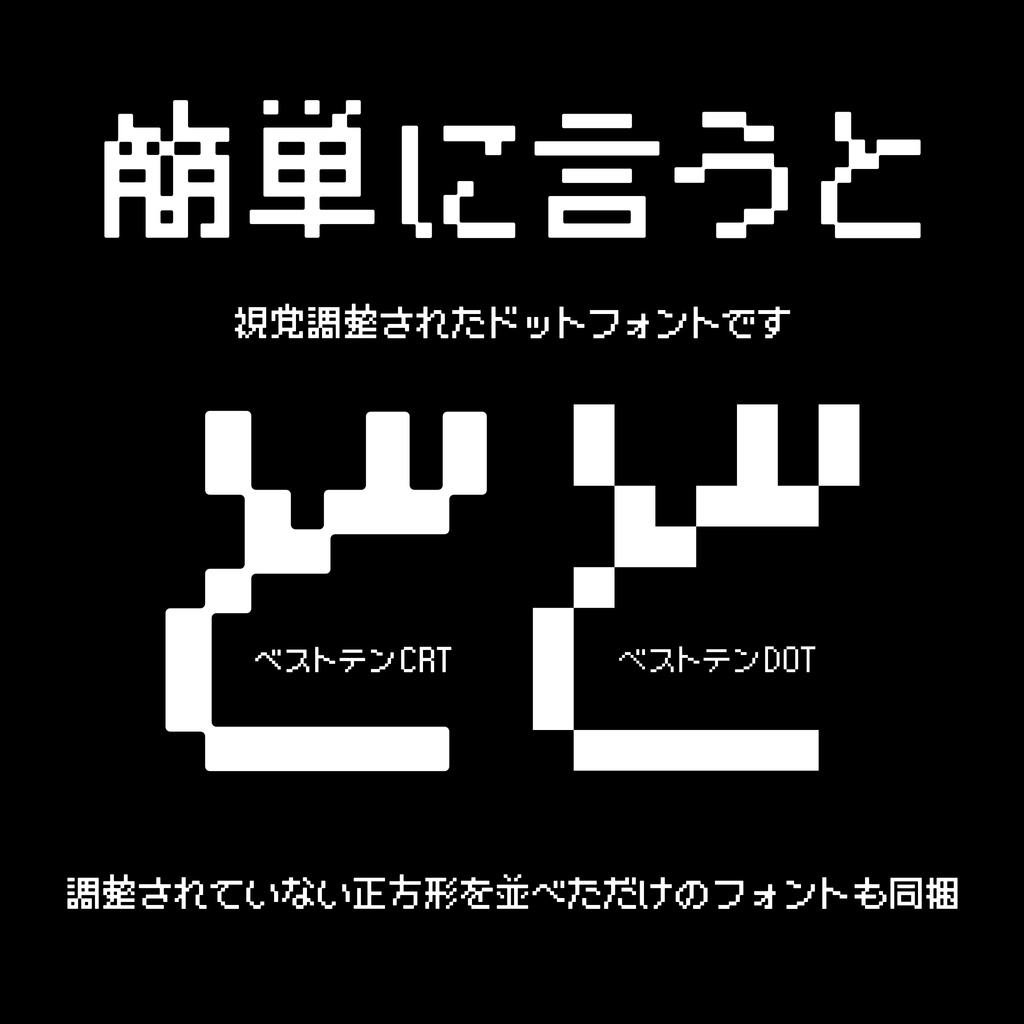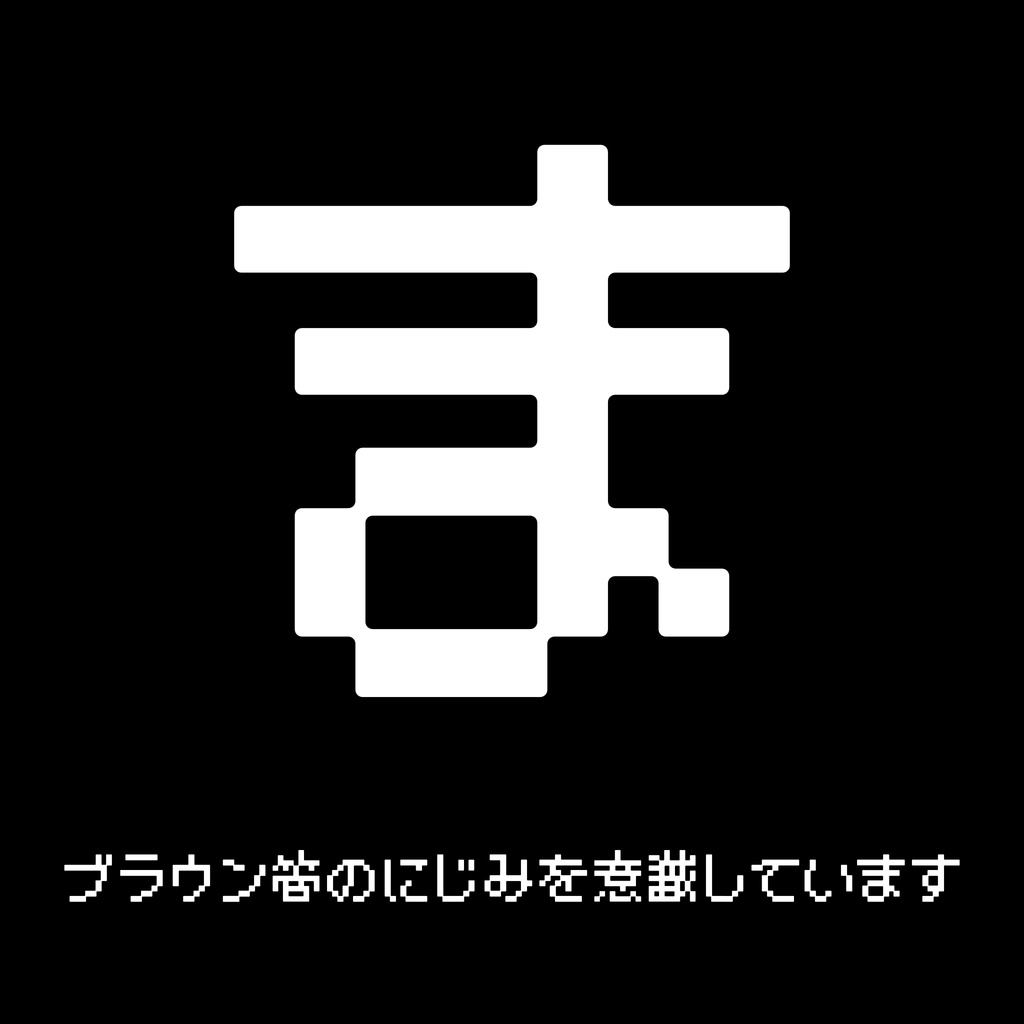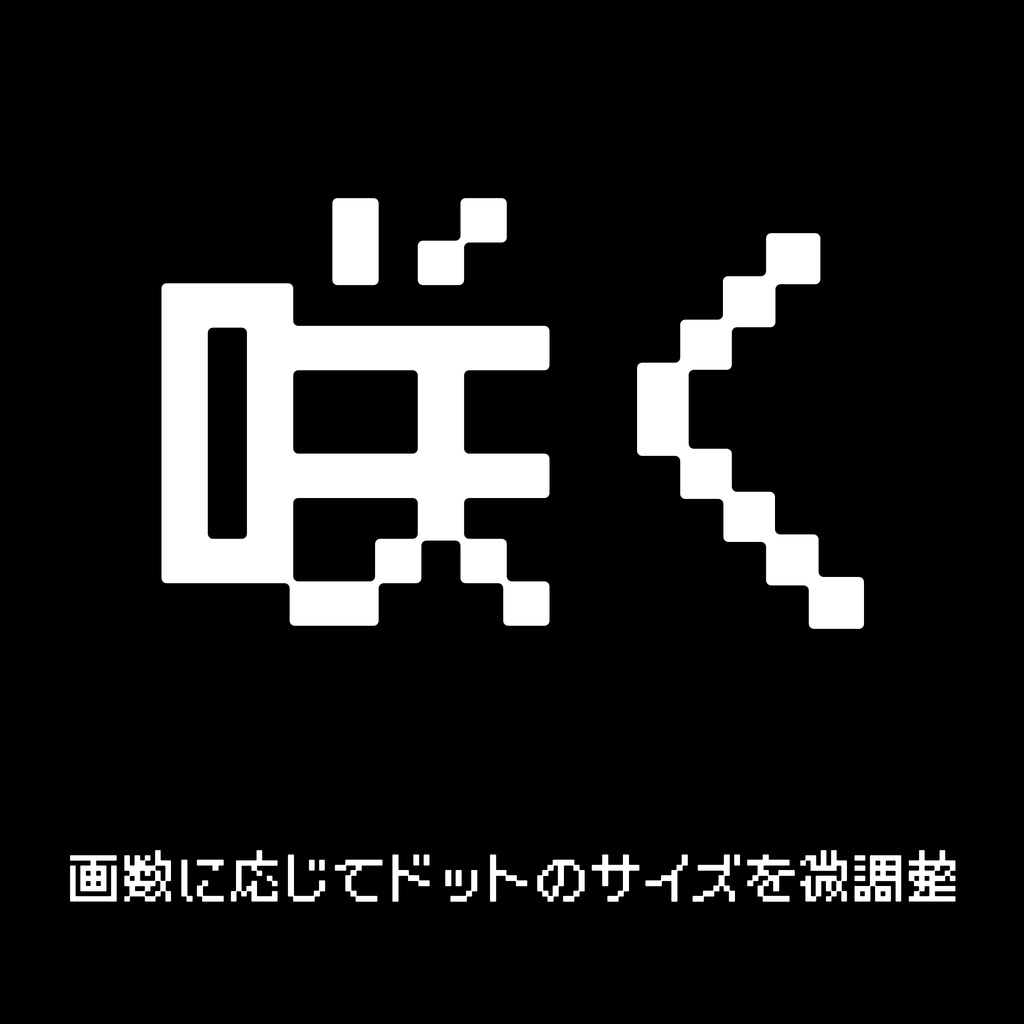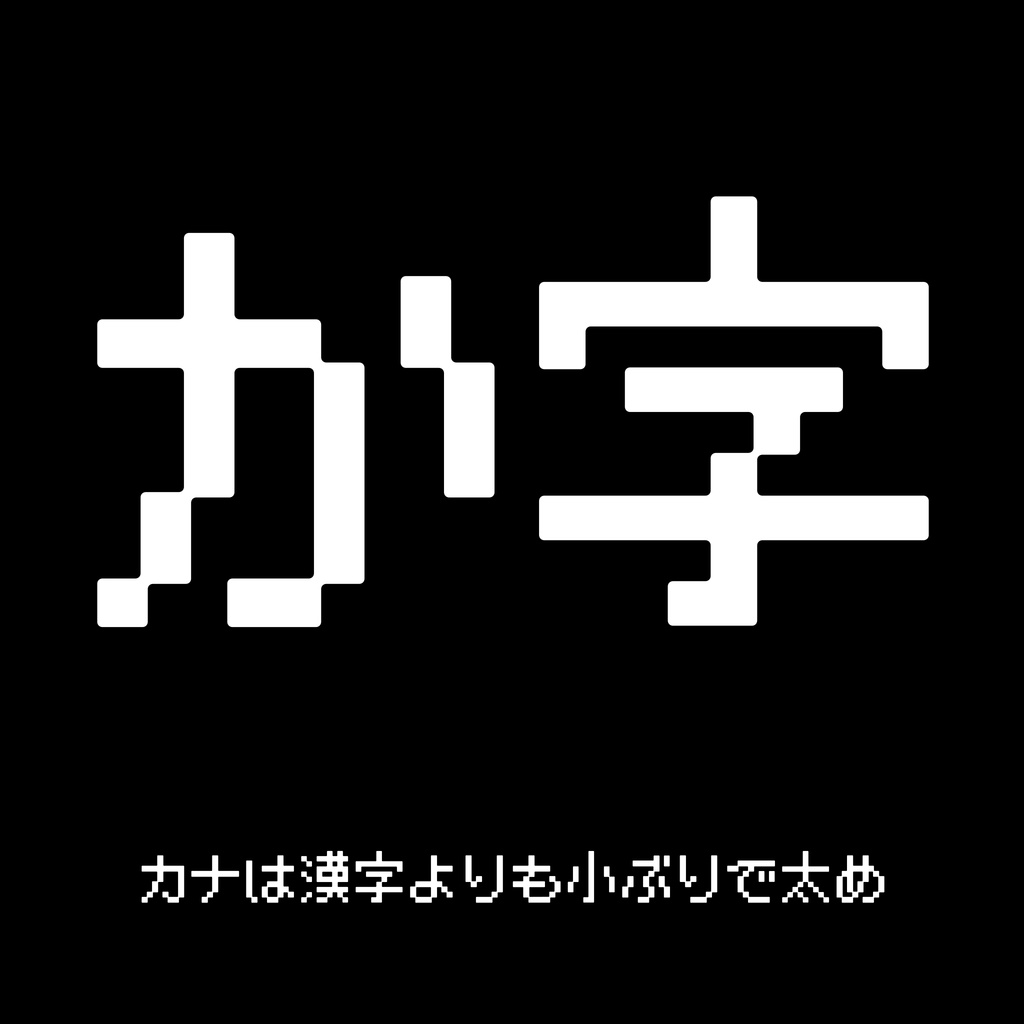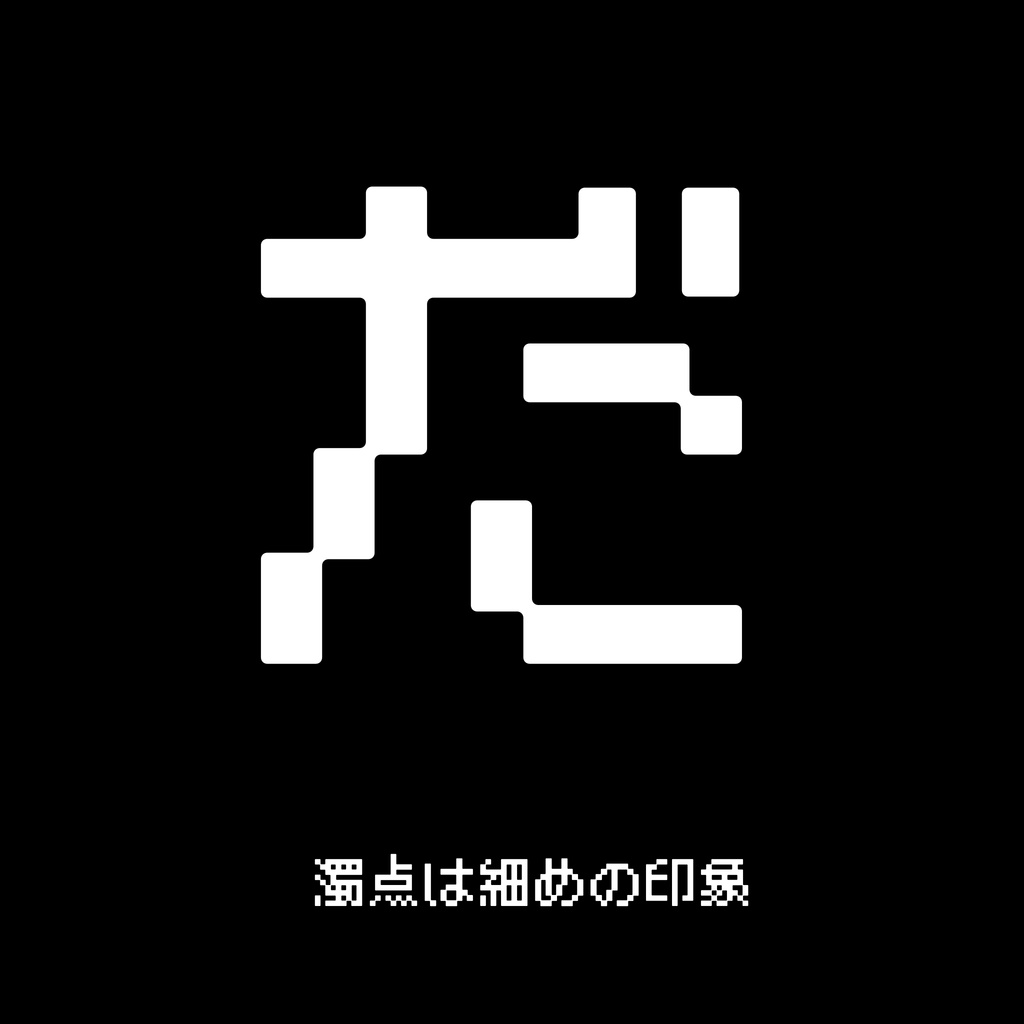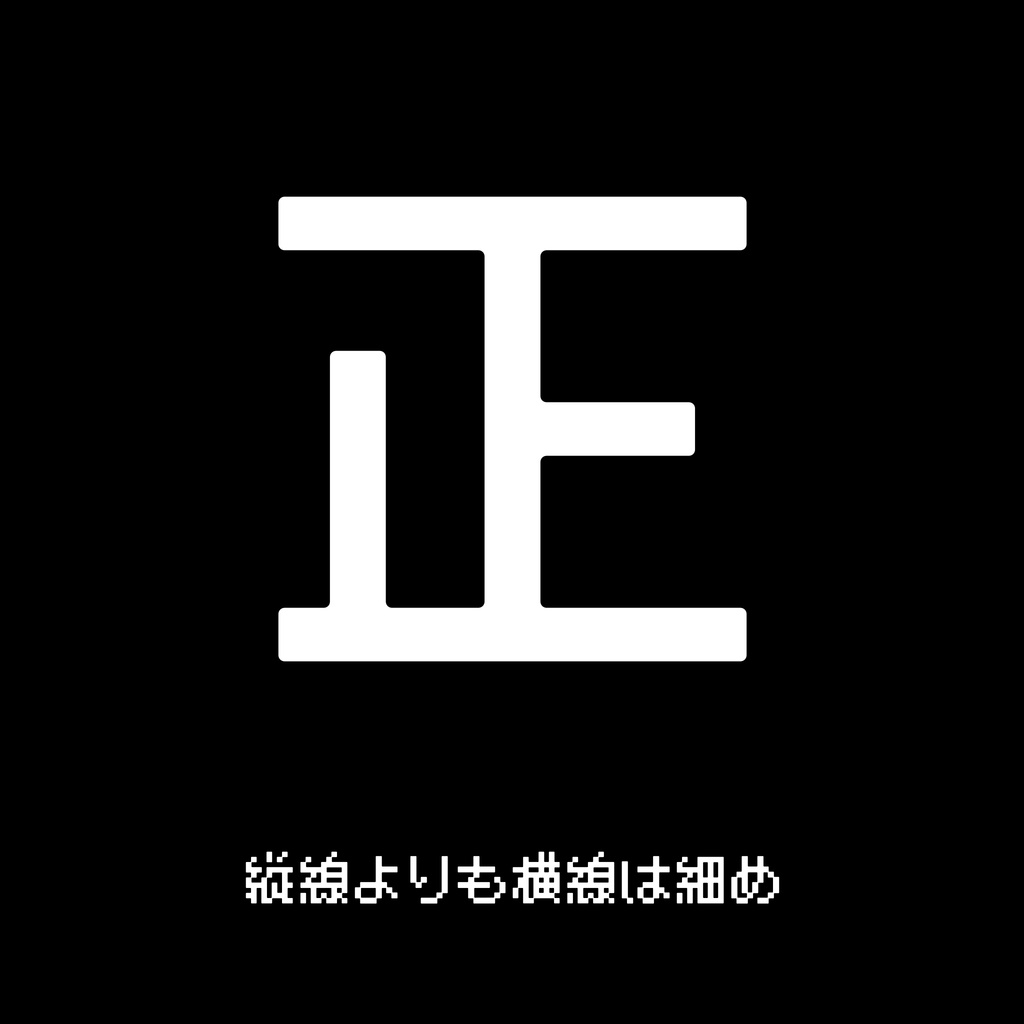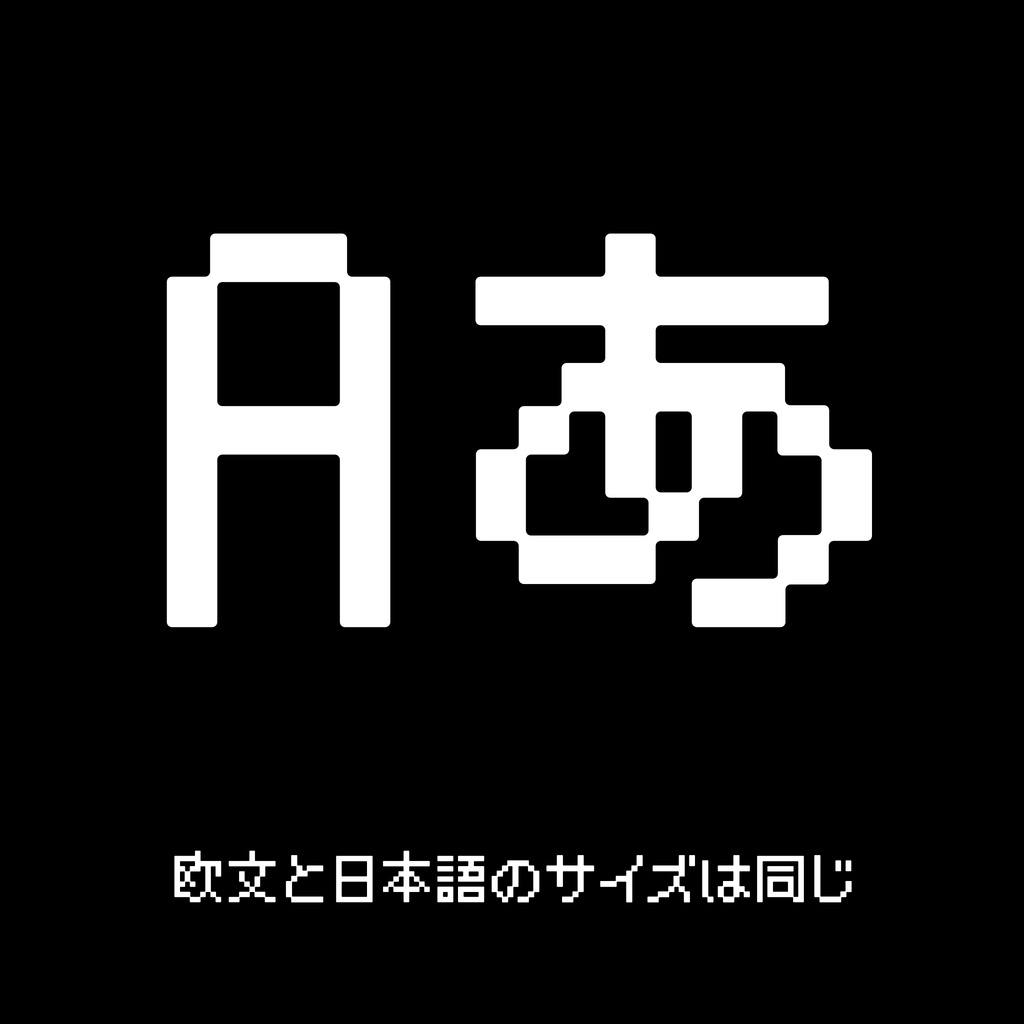
ベストテンFONT フリーフォントのベストテンは無料でダウンロードできるドットフォント。商用・非商用問わず使用可能なので、安心してダウンロードしてください。 【特徴】 10×10のドットフォント。視覚調整と加工のされたベストテンCRTと、ドットを並べただけのベストテンDOTの2種類。簡単に言うとそのまま使うだけでレトロなゲームやコンピューターっぽくなるベストテンCRTと、純粋にドットフォントとして使えるベストテンDOTのセットです。 ひらがな、カタカナ、欧文をオリジナルで制作し、残りの部分をM+ BITMAP FONTSの派生フォントPixelMplus10で補いました。 【フォントの商用利用・プログラムへの埋め込みについて】 作成した印刷物およびデジタル・コンテンツにつき、その商用・非商用にかかわらず印刷、放送、通信、各種記録メディアなどの媒体の形式も問わず、使用をすることができます。プログラムへの埋め込みが可能です。 【形式】 Format: Open Type License: フリーフォント(商用可) 収録字数:約7200字 M+ BITMAP FONTS派生のフリーフォントになります。 フォントは以下のライセンスに準じます。 Copyright(c) 2021 M+ FONTS PROJECT 当フォントはFontlabStudio、Glyphs、武蔵システム(http://opentype.jp/)OTEditで作成しました。 ⚠️このフォントは自由に動画に使えるフォントです。ご利用の際は次のクレジットを入れていただけると、ものすごく喜びます! –––––––––––––––––––––––––––––– フォント:ベストテンFONT フリーダウンロード:https://flopdesign.booth.pm/items/2747965 –––––––––––––––––––––––––––––– フォローしてください。 Instagram ▶ https://www.instagram.com/flopdesign.font/ X ▶ https://twitter.com/flopdesign